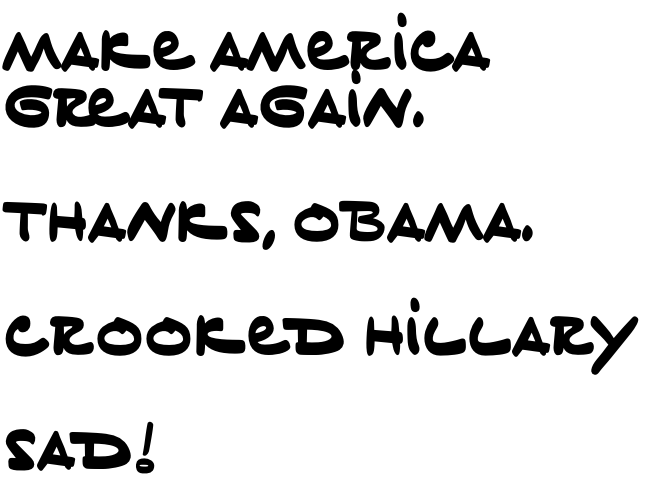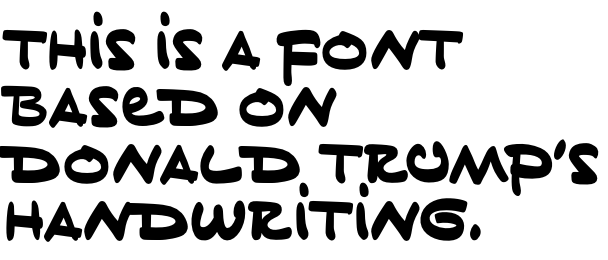
도널드 트럼프 미국 대통령의 손글씨를 본 딴 폰트
유명인사들은 작은 습관 하나 까지도 큰 이슈를 불러오기 마련이다. 미국 대통령 도널드 트럼프도 예외는 아니다. 지난 해, 방한해 청와대 방명록에 남긴 트럼프 대통령의 손글씨가 큰 화제가 되었는데 , 네티즌들은 ‘어린 아이 글씨 같다’, ‘얼굴과는 다르게 귀여워서 놀랍다’ 등의 반응을 쏟아냈다. 그런데 재미있는 것은 트럼프 대통령의 손글씨가 폰트 파일로도 존재한다는 것.
트럼프 대통령의 손글씨는 미국 매체 버즈피드의 타이포그래퍼 마크 데이비스(Mark Davis)가 2016년 10월 제작해 배포했다. 이 폰트의 이름은 ‘작은 손(TINY HAND)’이다. 트럼프 대통령의 체격에 비해 유난히 작은 손의 특징을 따온 것이다. 버즈피드는 이 폰트를 무료로 공개하며 ‘bigly’라고 발음하는 트럼프의 언어 습관을 꼬집기도 하였다.
한편, 트럼프 대통령은 대통령이 되기 전 부동산 재벌 시절부터 자신에 대한 기사를 인쇄해 직접 손글씨로 반박하는 것으로 유명했다. 그러나 대부분 일방적으로 기자나 언론사를 비방하거나 무조건 부정하고 윽박지르는 내용이었기 때문에 그의 주장대로 기사가 수정되거나 언론사로부터 사과를 받은 적은 거의 없다고 한다.